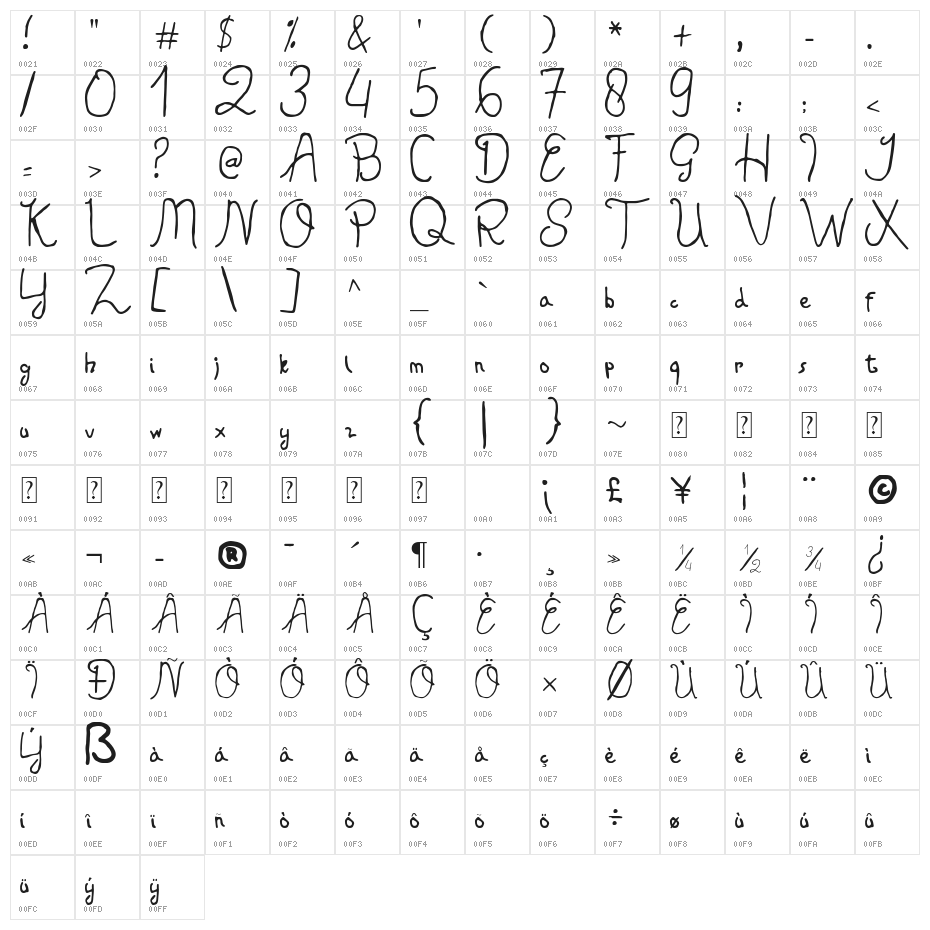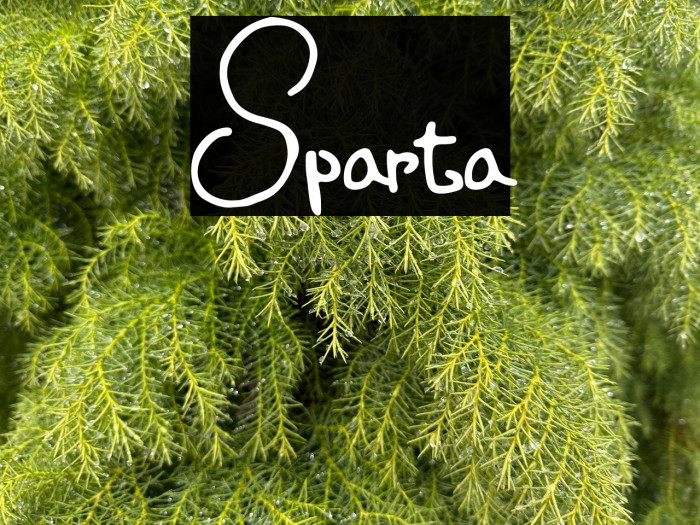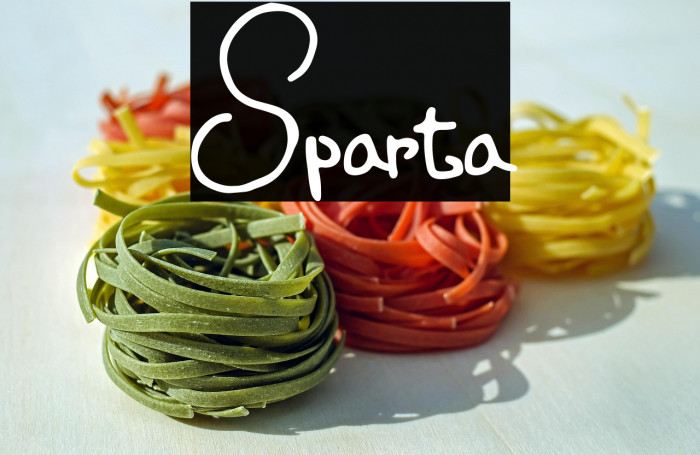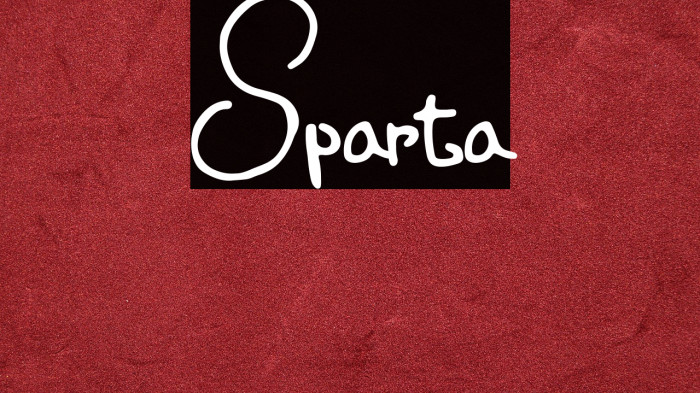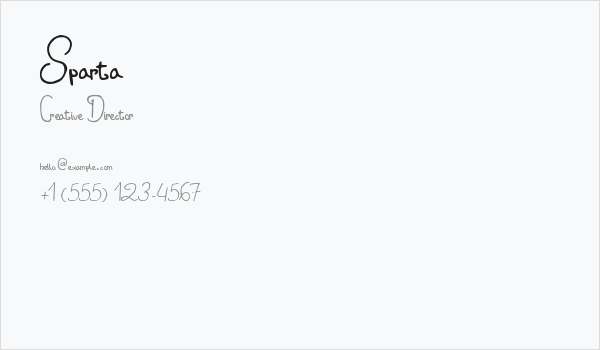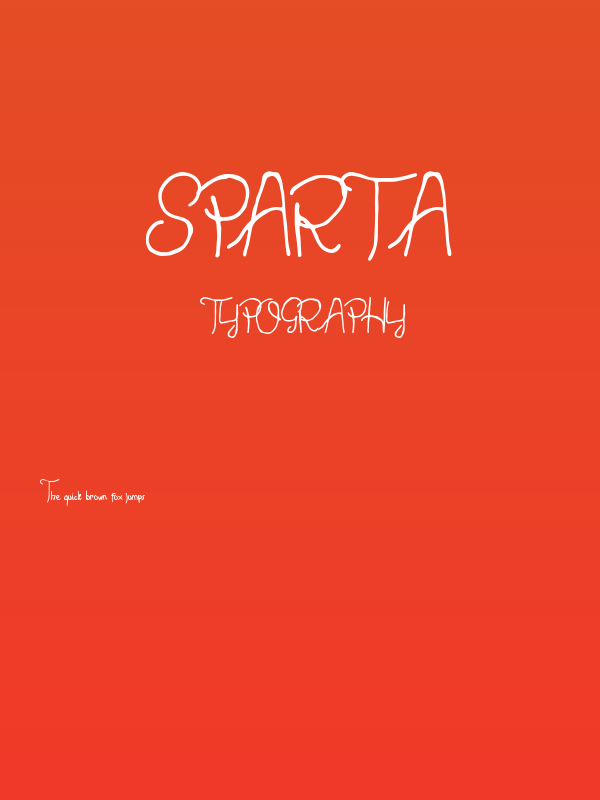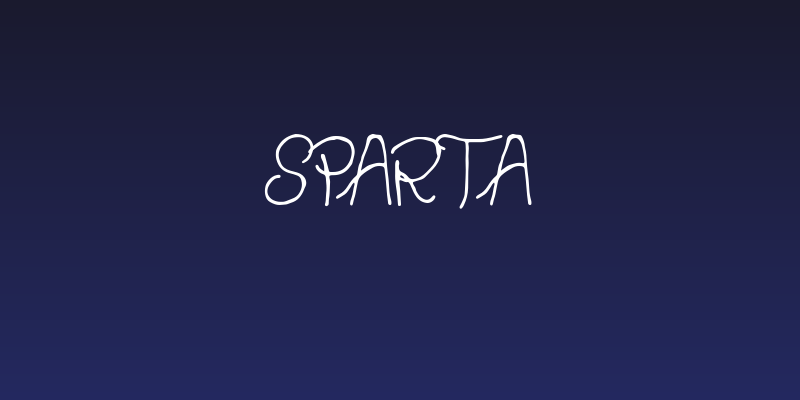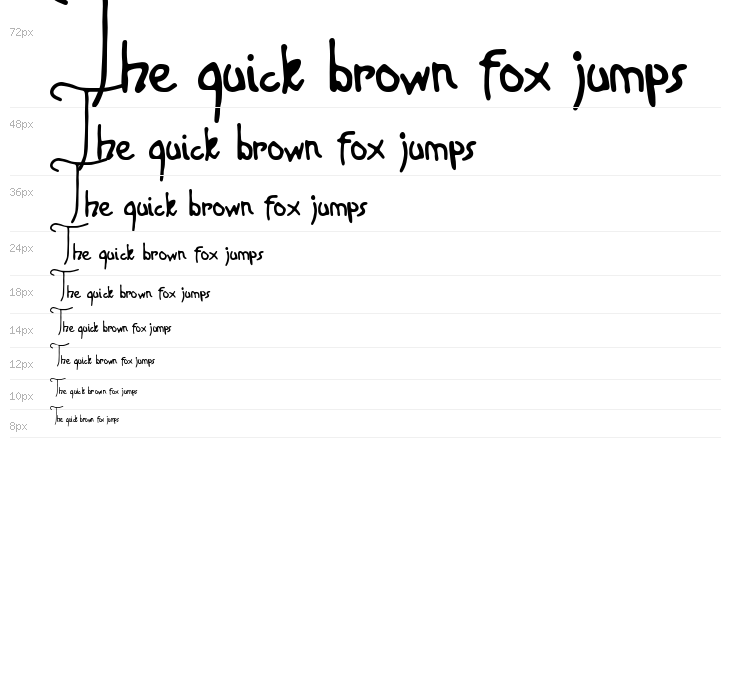
Sparta Font
| Область применения | Headlines, Logos, Creative projects |
| Рекомендуемые проекты | Ideal for greeting cards, children's books, playful branding, and creative posters. |